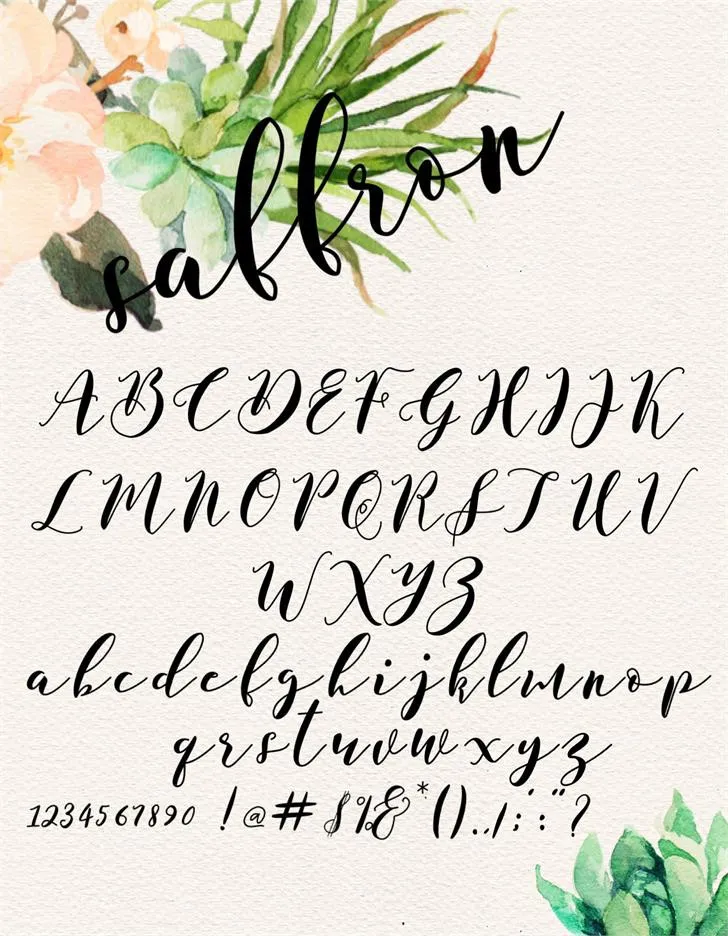
A fonte ‘Saffron Script Font’ foi criada pelo designer SarahTaylorDesigns com a intenção de ser fluida e moderna. Este tipo de texto é perfeitamente encantador e elegante ao mesmo tempo, oferecendo um toque leve que não se sobrepõe à sua mensagem. Ideal para aplicação em cartões de festa, convites, mídia online, logotipos, assentamentos e qualquer coisa mais que possa imaginar. A ‘Saffron Script Font’ é uma ótima escolha para quem busca um design suave e inovador, adaptável a diversos usos. Como designer de recursos gráficos atento às tendências modernas, esta fonte parece perfeitamente alinhada com o estilo e necessidades de muitas pessoas. Ela é capaz de trazer a personalidade ideal aos seus projetos digitais ou físicos.